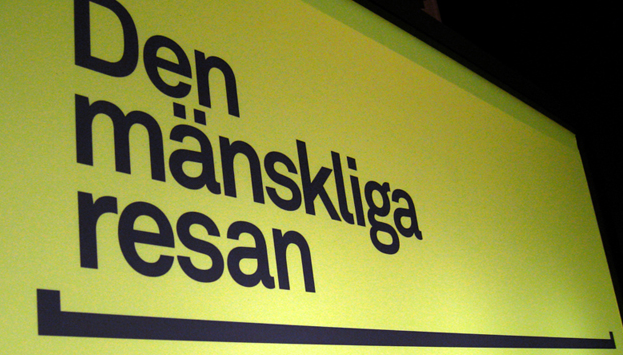
Ich tippe auf Akkurat von Lineto (die Fette). Sauschön und leider teuer.
Darf ich fragen, was das für ein Bild ist bzw. wo sie so eingesetzt wurde? Sieht sehr fein aus.